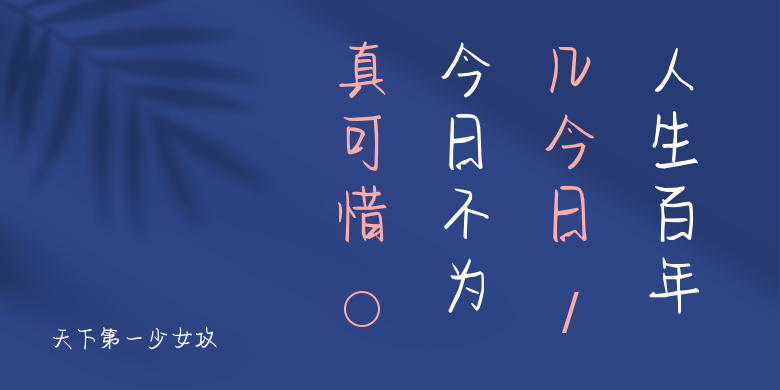
天下第一少女攻
天下第一少女攻,这款字体结构工整、笔画清晰,兼顾美观与易读性,适用于标题、正文、海报、包装、LOGO 等多种场景。字形优雅稳定,风格百搭耐看,适配日常排版与创意设计,让文字呈现更舒适、更具质感。天下第一少女攻一笔一画,皆是细节,以均衡的比例、流畅的线条打造舒适视觉体验,字形端正大气,风格简约现代。无论是商业设计、品牌宣传还是日常排版,都能轻松驾驭,让文字更有格调与力量。天下第一少女攻字体下载。